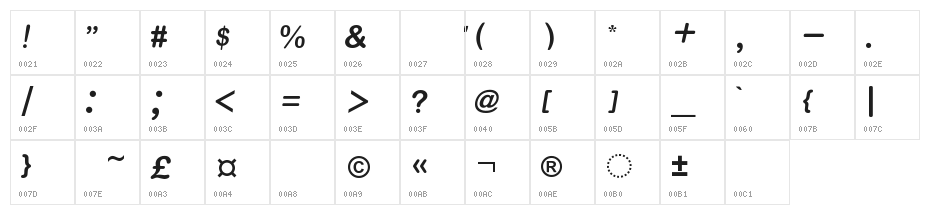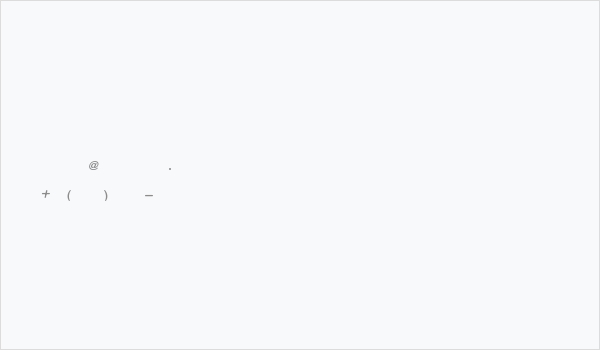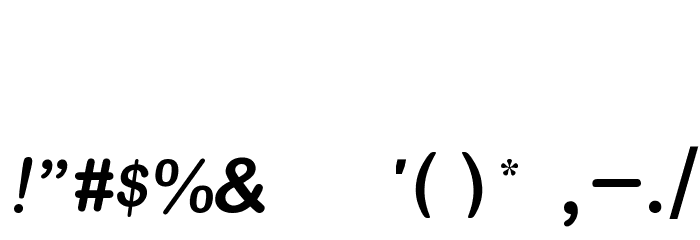
Sundanese Unicode Font
| Общий стиль | Traditional |
| Область применения | Cultural documents, educational texts, heritage projects. |
| Рекомендуемые проекты | Ideal for cultural preservation projects, educational materials, and any design work that aims to incorporate Sundanese heritage. |